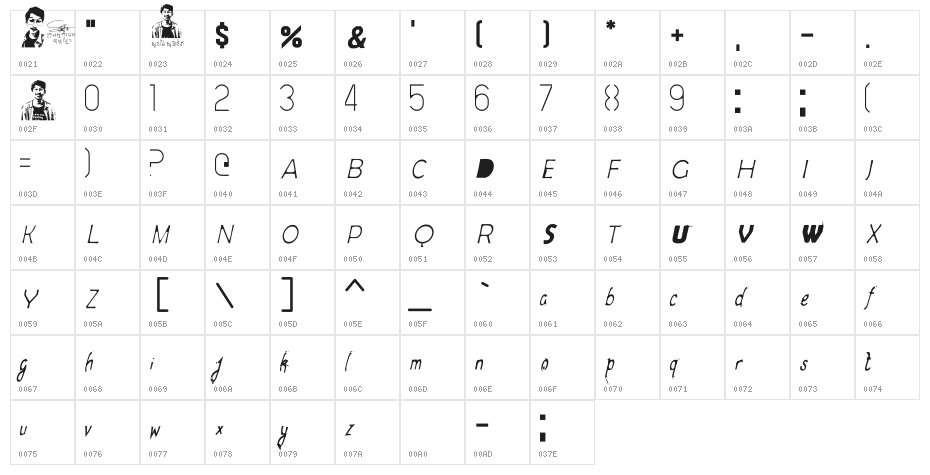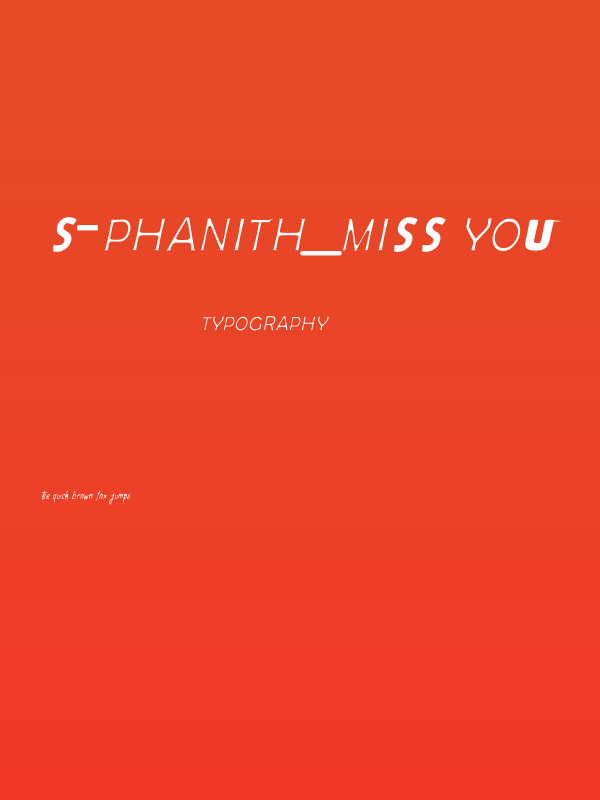
S-Phanith_miss you Font
| Stile generale | Modern, Decorative |
| Progetti proposti | Ideal for branding, advertising, posters, and creative design projects requiring a distinctive and artistic touch. |